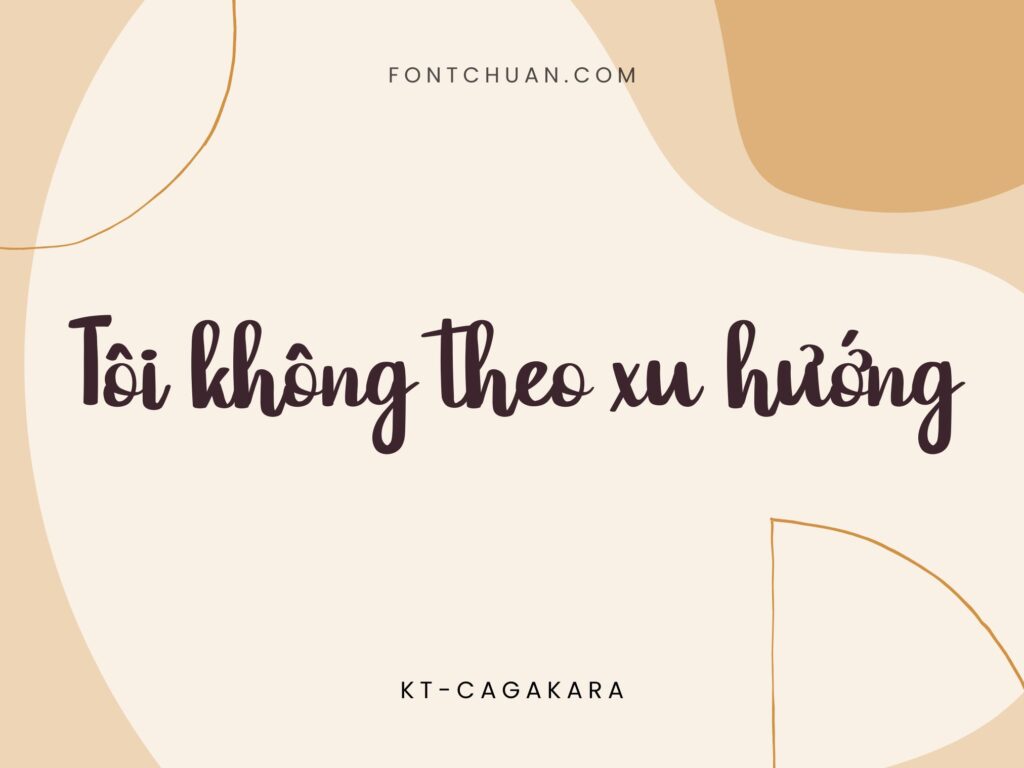
Font Cagakara Việt Hóa
Cagakara là một phông chữ script độc đáo được thiết kế bởi Eknoji Studio, mang phong cách viết tay với các đường nét mềm mại và uyển chuyển. Phông chữ này phù hợp cho nhiều mục đích thiết kế khác nhau, từ dự án cá nhân đến thương mại. Phiên bản Cagakara đã được Việt hóa bởi KT Font, hỗ trợ đầy đủ các ký tự tiếng Việt, mang lại trải nghiệm gõ chữ trọn vẹn cho người dùng Việt Nam. Ngoài tiếng Việt, phông chữ này còn hỗ trợ nhiều ngôn ngữ khác, mở rộng khả năng ứng dụng trong các dự án quốc tế. Việc Việt hóa được thành viên của Font Chuẩn chọn lọc và sưu tầm, nhằm đáp ứng nhu cầu bạn đọc và ứng dụng thực tế vào các dự án thiết kế.
Về đặc điểm thiết kế, Cagakara thuộc loại phông chữ script với cấu trúc chữ mềm mại, tạo cảm giác như chữ viết tay tự nhiên. Độ tương phản nhẹ và độ dày vừa phải giúp phông chữ trở nên dễ đọc và thu hút. Các ligature được thiết kế tinh tế, tạo sự liền mạch và thẩm mỹ cao cho văn bản. Với những đặc điểm trên, Cagakara phù hợp cho các ứng dụng như thiết kế logo, tiêu đề, thiệp mời, bao bì sản phẩm và các dự án sáng tạo khác. Phông chữ này cũng thích hợp cho các thiết kế cần sự mềm mại và nghệ thuật, như áp phích quảng cáo, bìa sách và các sản phẩm thương hiệu cá nhân. Về ngành nghề, Cagakara đặc biệt phù hợp với lĩnh vực quảng cáo, spa, ẩm thực, thiệp cưới và ảnh cưới. Sự tinh tế và nét chữ uyển chuyển giúp phông chữ này dễ dàng hòa nhập vào nhiều phong cách thiết kế khác nhau, từ cổ điển đến hiện đại.
Bên cạnh các ứng dụng nghệ thuật và cá nhân hóa, Cagakara còn là một font valentine lý tưởng để thiết kế các sản phẩm lãng mạn và ngọt ngào, như thiệp Valentine, banner hay poster dịp lễ tình nhân. Với các đường nét mềm mại, uyển chuyển và tinh tế, font này giúp các thiết kế vừa thanh lịch, vừa ấm áp, tạo cảm giác gần gũi và thân thiện, phù hợp cho các dự án sáng tạo mang chủ đề tình yêu và các dịp đặc biệt.